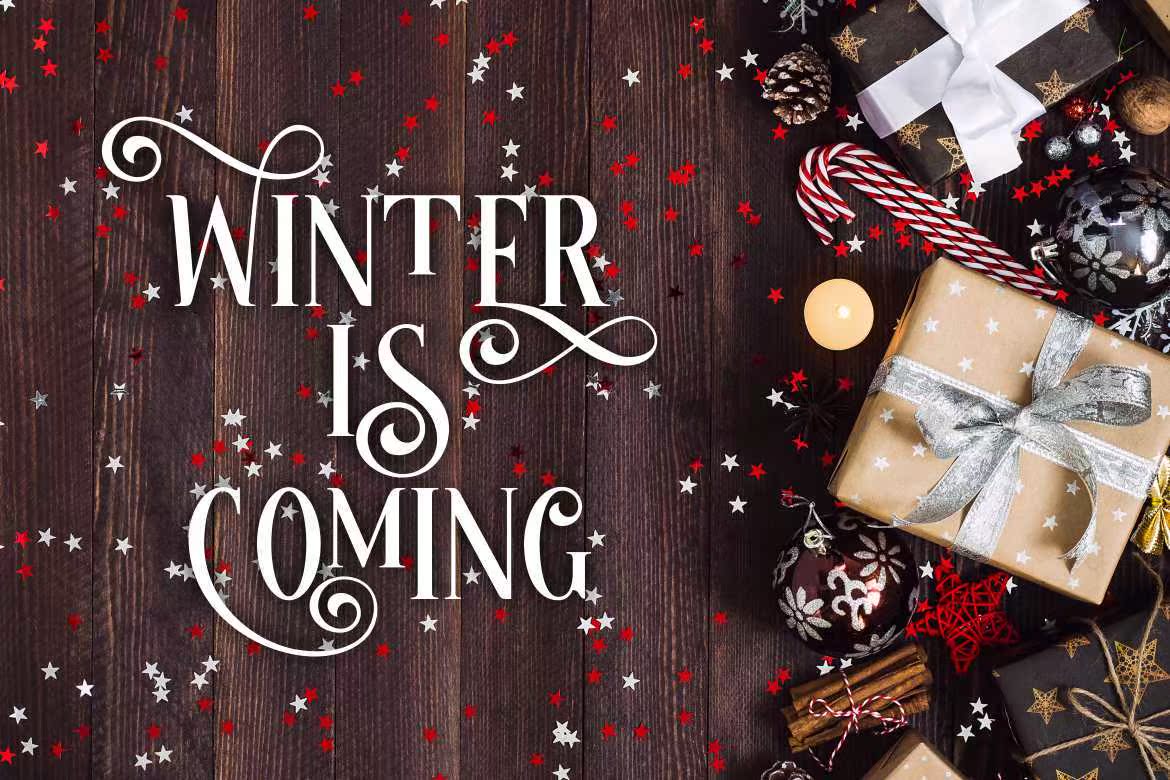
MagicsParklesacurl和Unseriffont。此脚本集是完美的,适用于类似于RTS或贺卡的礼品。也适用于婚礼、品牌推广、文具、博客设计、定制艺术、定制邮票、定制浮雕、,或任何设计目的。此包装包括一些有趣的连接线和替代选项。MagicsParklesacurl和Unselfont。此系列的脚本非常适合于以卡片或贺卡形式制作的产品。也适用于婚礼、品牌推广、文具、博客设计、定制艺术、定制邮票、定制浮雕、,或任何设计目的。此包装包括一些有趣的韧带和替代物。